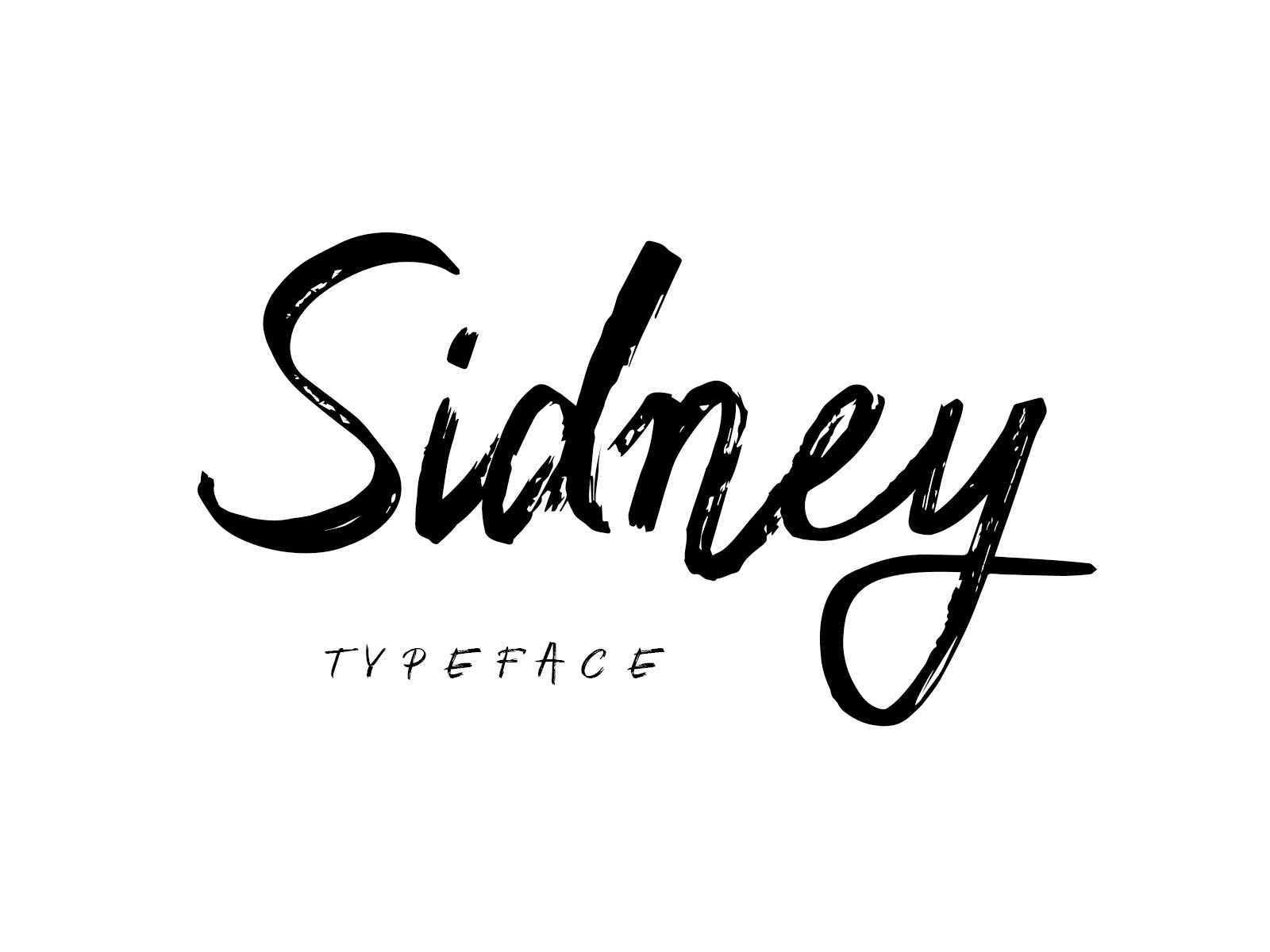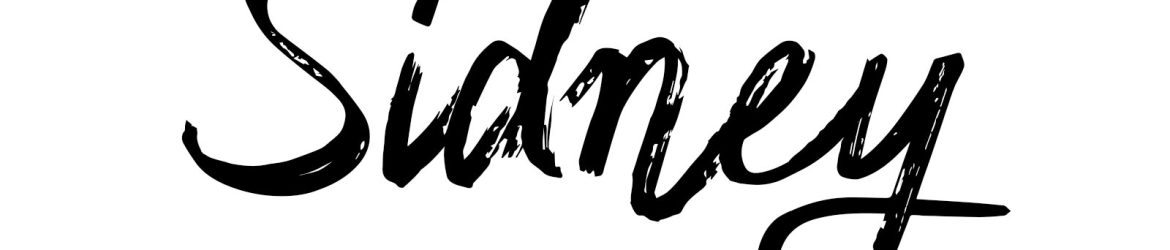
Sidney Script Free Typeface – Download Grátis
A fonte Sidney Script é uma nova e linda tipografia de script que incorpora dois estilos: um clássico e elegante (fontes com capas limpas e retas) e outro desorganizado e caprichado (com letras sujas e irônicas). Essa dualidade permite que você faça uma combinação única de design, resultando em algo que se destaca. A fonte Sidney Script oferece 300 glíficos, ligaturas e letras extras para o seu uso. Use-a para a sua marca, web e impressão. Este recurso é perfeito para quem busca dar um toque único e elegante em seus projetos.